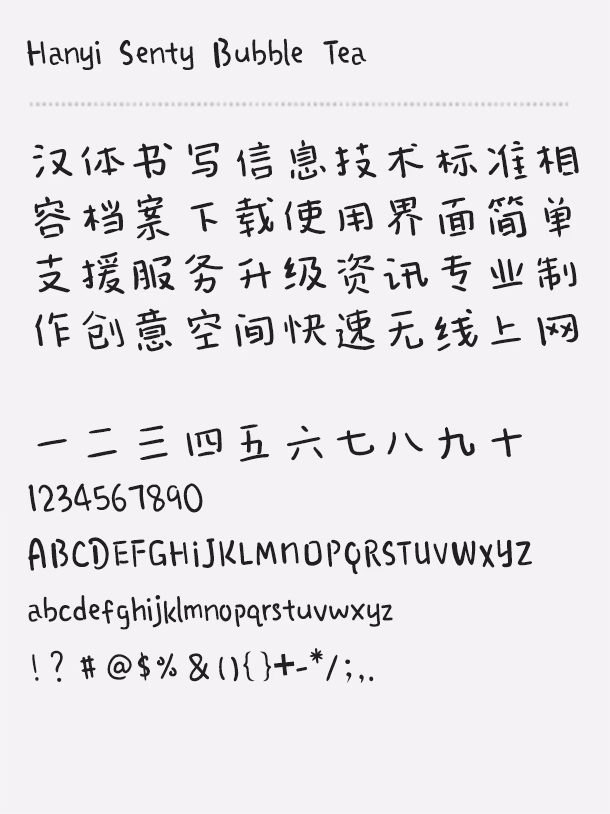
At integrere tekst på forskellige sprog er en almindelig opgave for designere og fotografer, og kinesisk byder på en særlig visuel rigdom. Kinesiske tegn har en lang historie og en kompleks struktur, der kræver specifikke skrifttyper for at blive gengivet korrekt og æstetisk tiltalende. Forståelse af, hvordan man får disse skrifttyper til at fungere i dine designværktøjer, som Adobe Photoshop, og kendskab til deres karakteristika, er afgørende for at skabe autentiske og professionelle resultater.
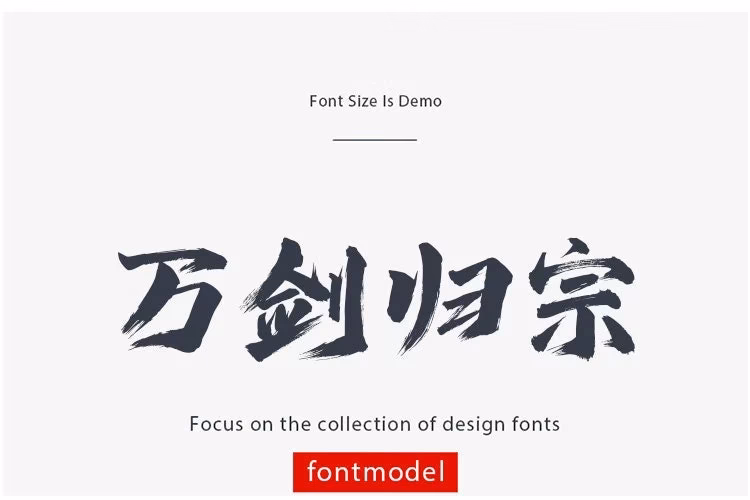
Hvad Kendetegner Kinesiske Skrifttyper?
Når man taler om skrifttyper til kinesiske tegn, er der en dominerende stil, der ofte bruges i trykte medier, kendt som Ming eller Song. I Japan kaldes denne stil for Mincho, og i Korea for Myeongjo. Denne stil er den mest udbredte til brødtekst i bøger, aviser og mange andre trykte materialer på kinesisk og japansk.
Ming/Song-skrifttyper har en række karakteristiske træk, der adskiller dem fra mange vestlige skrifttyper:
- De følger den grundlæggende struktur fra den almindelige skriftstil (regular script).
- De har en tydelig kontrast mellem tykke vertikale streger og tynde horisontale streger.
- Ved enden af enkeltstående horisontale streger finder man små trekanter, der på japansk kaldes uroko (鱗), hvilket betyder 'fiskeskæl'. Disse fungerer lidt ligesom seriffer i vestlige skrifttyper. De er en trykt analogi til den lille prik eller fortykkelse, der opstår, når man pauser sin pensel (頓, dùn) i kalligrafi for at forstærke begyndelsen eller slutningen af et strøg – en teknik, der er karakteristisk for regular script.
- Der er generel geometrisk regelmæssighed i tegnes opbygning.
På grund af deres variable stregtykkelse og de karakteristiske afslutninger (uroko/seriffer), kan Ming/Song-stilen sammenlignes med vestlige seriffer, mens den østasiatiske gotiske stil (Gothic/Hei), som er mere ensartet i stregtykkelse, kan sammenlignes med vestlige sans-serif skrifttyper.
Variationer i Kinesiske Tegn
Det er vigtigt at bemærke, at der findes variationer i, hvordan det samme kinesiske tegn kan skrives. Disse kaldes samlet for 'variant Chinese characters'. Nogle forskelle skyldes forenkling af tegn (som i Folkerepublikken Kina), mens andre er rent ortografiske forskelle i stregføring og form.
- Historisk set stammer stregføringen i gamle Ming-skrifttyper fra stilen brugt i Kangxi-ordbogen.
- I Fastlandskina er de moderne standardiserede tegnformer specificeret i 'List of Commonly Used Characters in Modern Chinese'. Nogle tegn heri afviger fra Kangxi-formerne enten fordi de er forenklede, eller fordi de bruger en anden variant eller ortografi.
- I Taiwan specificerer 'Standard Form of National Characters' de moderne standardiserede former. Denne standard læner sig mere op ad den almindelige skriftstil og reformerer Ming-skrifttyper baseret på denne kalligrafiske stil, hvilket har affødt kritik.
- Efter kanji-reformerne i Japan efter krigen kaldes de fleste tegn i Kangxi-stil for kyūjitai (gammel stil), mens de reformerede tegn kaldes shinjitai.
Ved at forstå, hvordan skrifttyper installeres på systemniveau, og ved at sætte sig ind i de grundlæggende karakteristika for kinesiske skrifttyper som Ming/Song-stilen og typografiske begreber som Tsume, kan du effektivt bruge kinesisk tekst i dine designprojekter i Photoshop og sikre, at dine budskaber ikke kun er korrekte, men også visuelt tiltalende og passende for den tilsigtede kontekst.